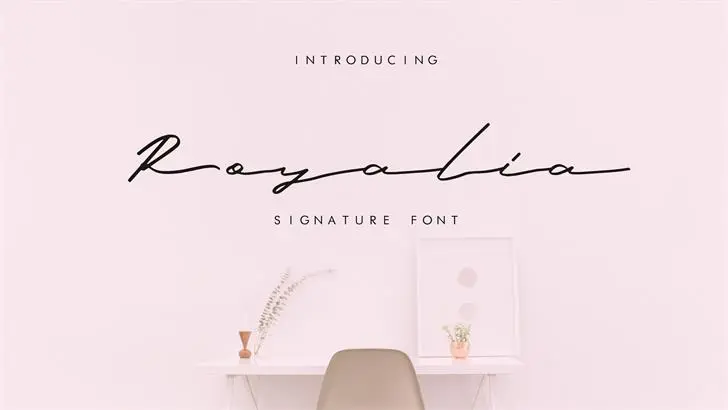
Introduzimos Royalia! Esta fonte foi projetada pela typefar, ideal para agradável escrita à mão. É perfeitamente adequada para uso em cartões de visita, calendários, marcapassos e outros materiais. Perfeita para invições, papelaria, cartão de visitas, blogs, design web, logotipos e anúncios. Royalia é uma demo de fonte, apenas permitida seu uso pessoal. Esperamos que você goste dela. A fonte ‘Royalia Signature Font’, categorizada como Script Fonts, foi criada pelo designer Hamilton.